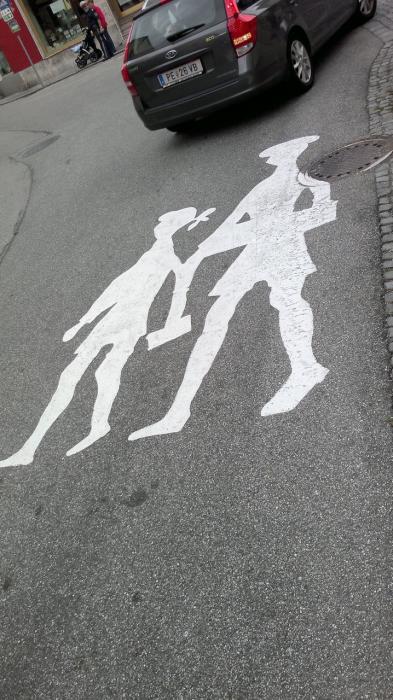
Straßenmarkierung
Was will uns diese Bodenmarkierung genau sagen? Sicher „Schule“ oder sowas. Aber das Mannschgerl rechts, was ist das für ein Typ? Was trägt der/die da mit sich?
Ein Bauchladen? Ist vielleicht der zuständige Dealer. Aber warum hat er dann einen Heiligenschein? Und dann dieser paternalistische Griff nach dem Oberarm des Mädchens. Ein Polizist mit Gipsarm und der Heiligenschein ist eine Polizeimütze? Aber kurze Hosen im Dienst? Rätsel über Rätsel.
Da ist dem Bauarbeiter der Farbkübel umgefallen. Die beiden Aussparungen würden ohne Stege nicht in der Schablone halten.
Wie "Achtung Kinder" weltweit aussieht, wurde hier zusammengetragen. Interessante Anatomie zuweilen … ;-)